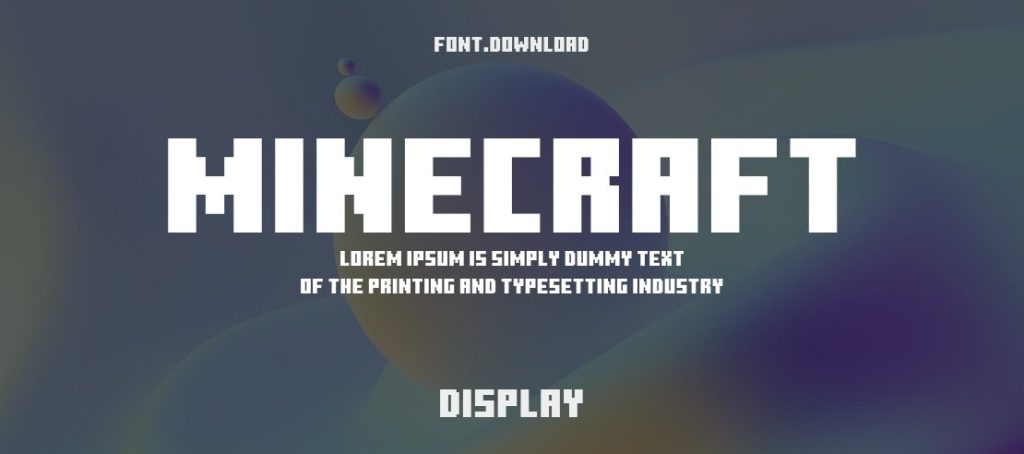
Tải Font Minecraft
Font Minecraft là một font chữ đặc trưng, gắn liền với tựa game nổi tiếng cùng tên, được biết đến với phong cách pixel art đặc trưng. Font chữ này tái hiện hoàn hảo giao diện pixelated của trò chơi, mang đến cảm giác hoài cổ và đơn giản, gợi nhớ đến thiết kế đồ họa 8-bit cổ điển. Font Minecraft là font chữ thuộc bộ font chữ design thường được sử dụng trong các thiết kế liên quan đến game, đặc biệt là khi muốn tạo ra sự kết nối trực tiếp với thế giới blocky và sáng tạo của Minecraft. Đây là lựa chọn lý tưởng cho các dự án thiết kế cần sự độc đáo, sáng tạo, và mang tính biểu tượng mạnh mẽ.